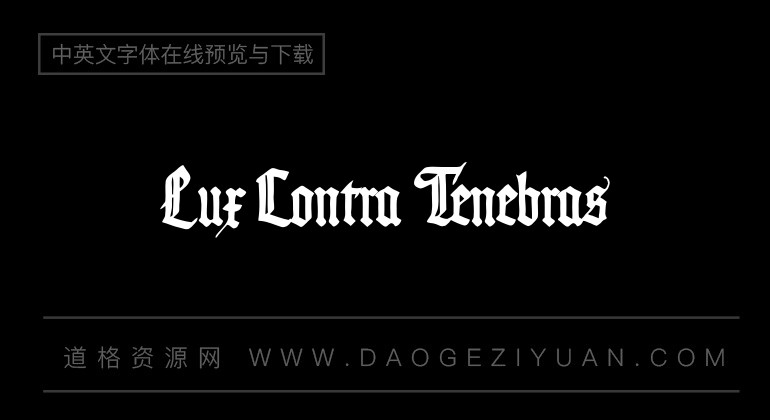
Lux Contra Tenebras 是一款由葡萄牙设计师Ricardo Santos设计的字体,它采用现代设计风格,拥有精致的线条和清晰的字形。它的设计灵感来源于古典文字的拉丁文,拥有细腻的结构和优雅的线条,使其能够融入任何现代风格的文字排版中。它的字体极具表现力,能够提升文字的美感和细节,使文字变得更加清晰和精致。内容介绍
Lux Contra Tenebras是一款非常不错的手写艺术字体,具有很好的视觉感,适合于文化类的宣传设计、商业类品牌的广告和产品包装设计以及个性化文字排版等较多场景。